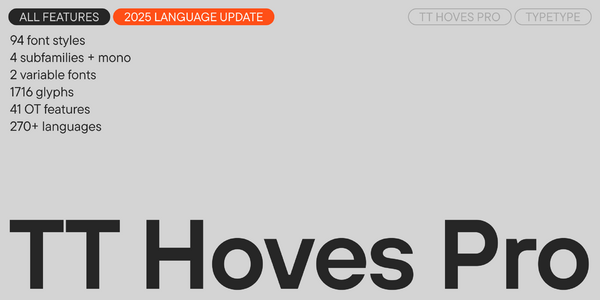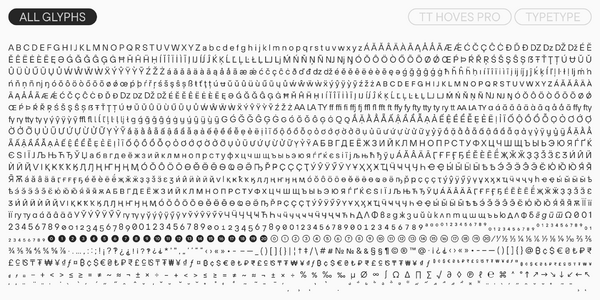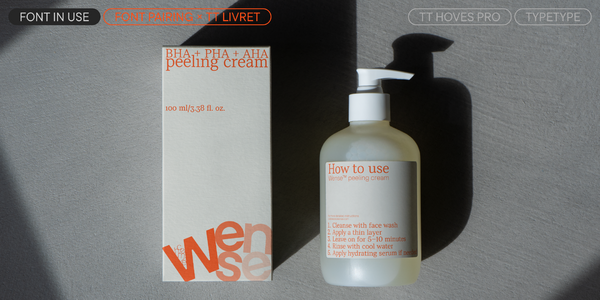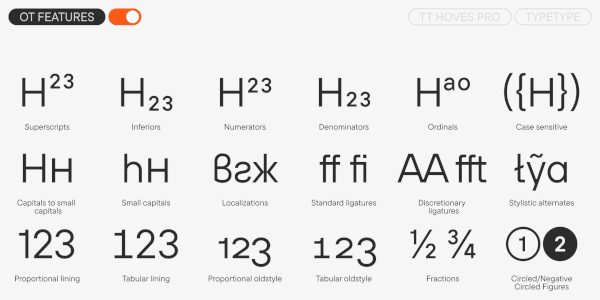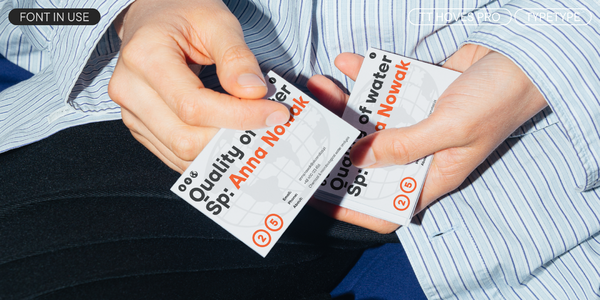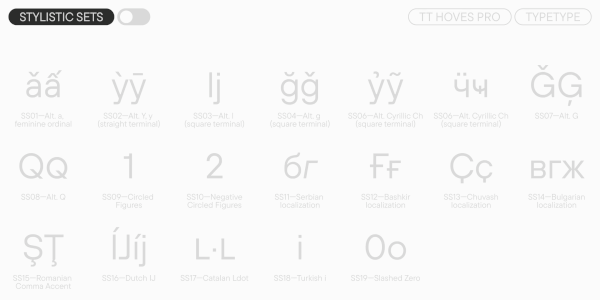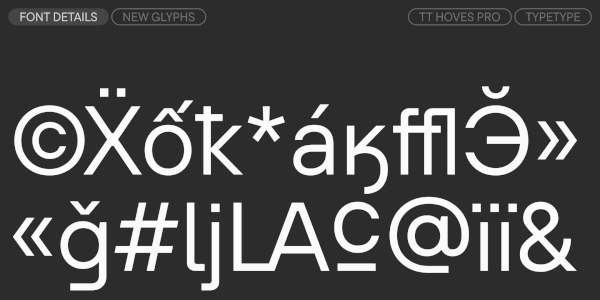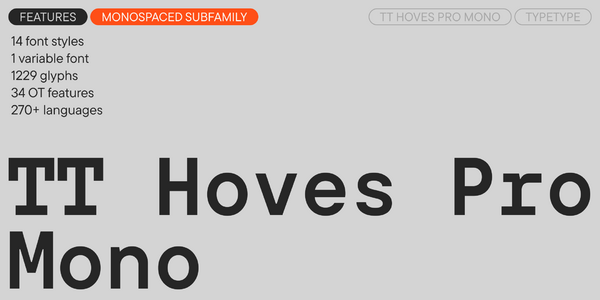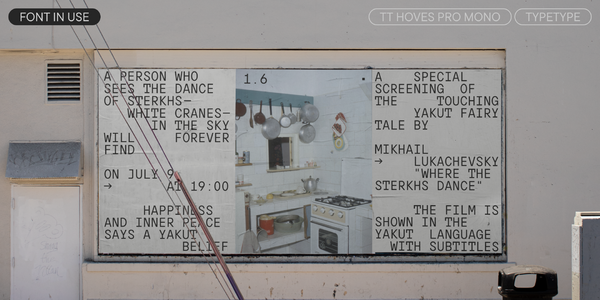
TT Hoves Pro
TT Hoves Pro — ТТ Ховс Про
Произносится «ТТ Ховс Про». «Hoves» — производное слово от horizontal (с английского «горизонтальный») и vertical (с английского «вертикальный»). «Pro» произносится как «про», и является разговорным сокращением слова «профессиональный». Буквы «TT» являются аббревиатурой названия компании.
TT Hoves Pro — скандинавский гротеск с нейтральным, но в то же время узнаваемым характером. Это удобный и функциональный, при этом стильный и эстетичный шрифт для различных задач.
TT Hoves Pro
Универсальный геометрический гротеск
TT Hoves Pro
TT Hoves Pro обладает явно выраженным характером, но при этом без слишком ярких всплесков или перегибов — он и не слишком нейтрален и в меру ярок. Мы хотели создать гротеск с узнаваемыми рисунком и геометрией, который бы отлично подходил для решения визуальных задач в архитектуре, дизайне, промышленности, точных науках, черчении, высокиx технологиях, исследованиях, статистике.